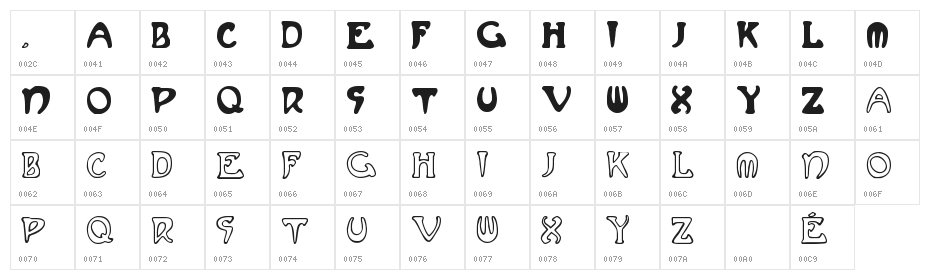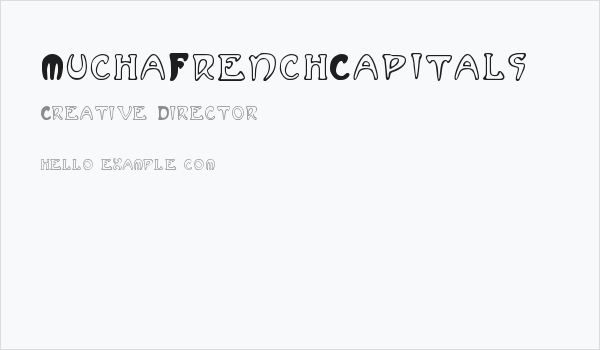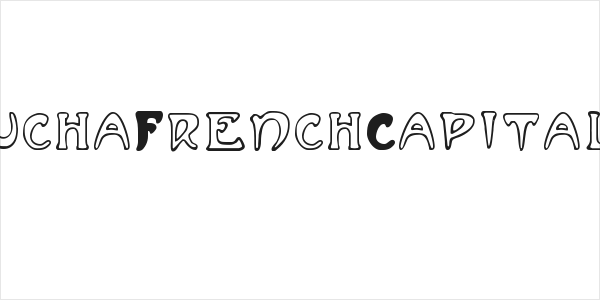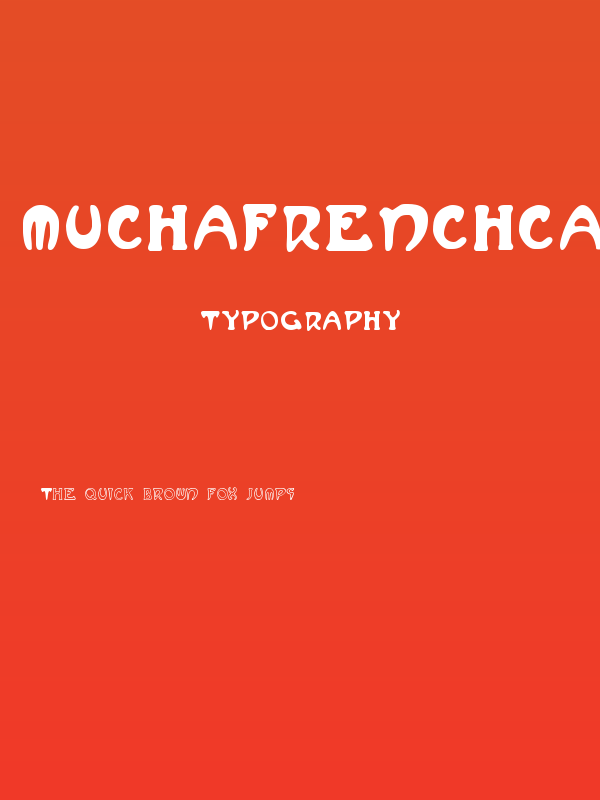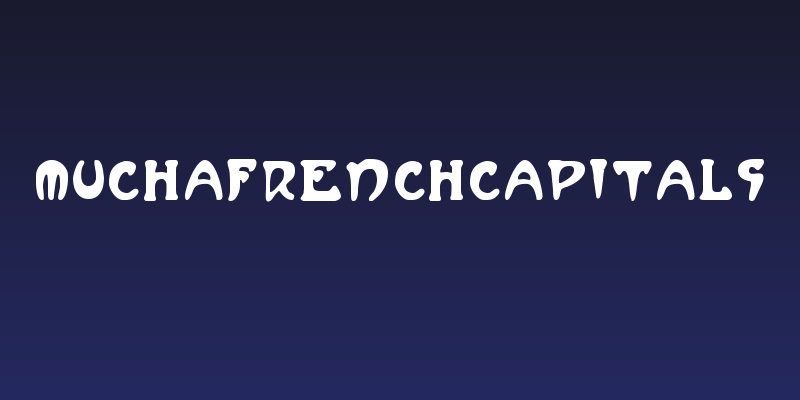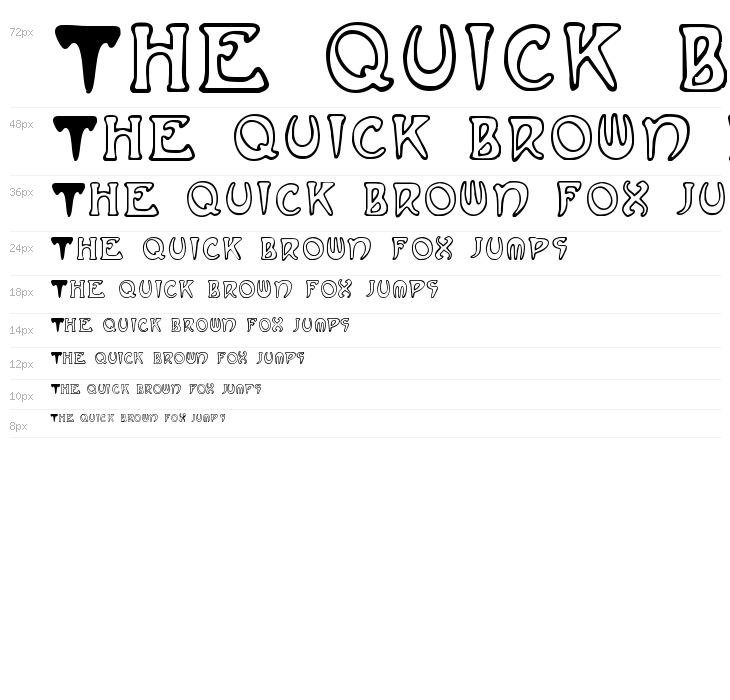
MuchaFrenchCapitals Font
✎ Art Nouveau
| Progetti proposti | Ideal for use in branding, posters, invitations, and any design project that seeks to convey elegance and artistic flair. |